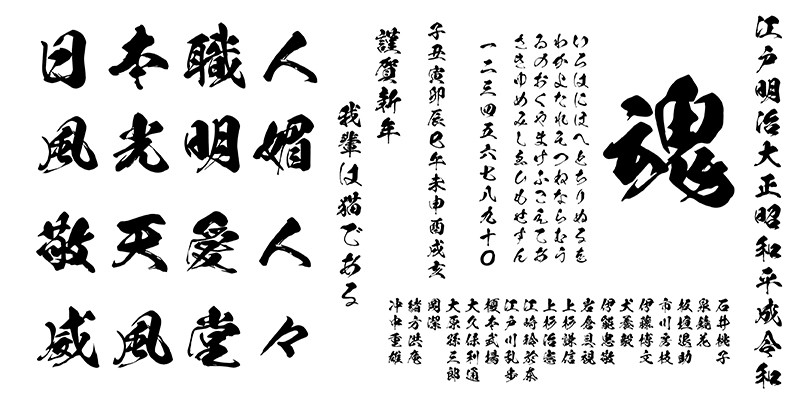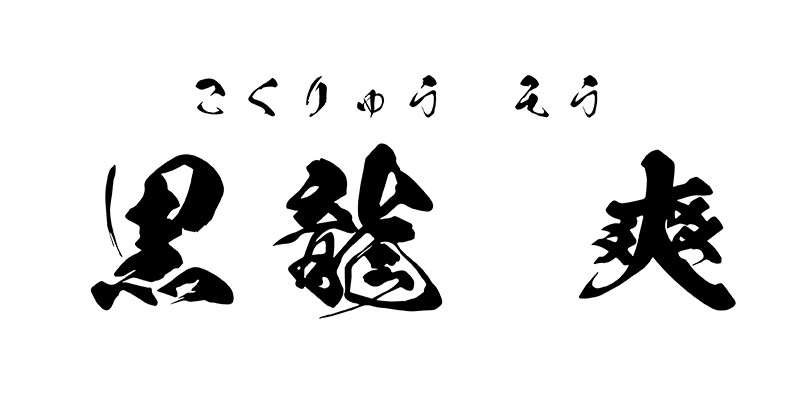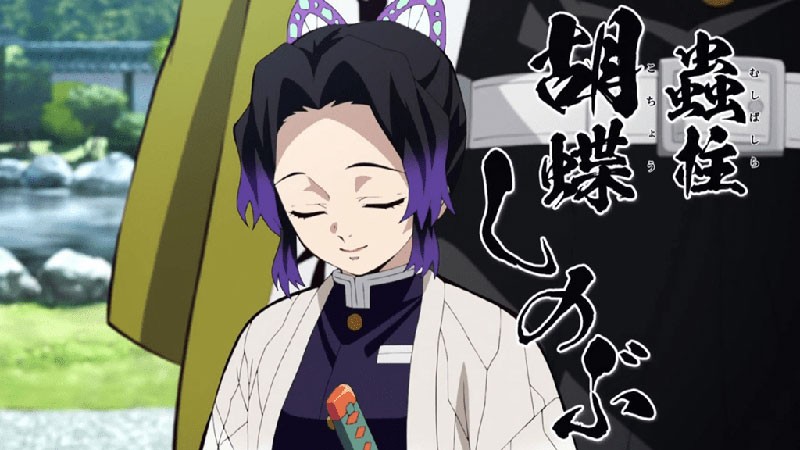
KokuryuSou《鬼灭之刃》动漫字体
Kokuryu-sou(黑龙)是一款高质量书法风格的日文字体,由 Eisen Tsunanori 綱紀栄泉 设计,手写绘制赋予了字体不平衡的特质。然而,当这些字母组合成文字时,却展现出强烈而和谐的视觉效果。ps字体名KSO黒龍N
KokuryuSou《鬼灭之刃》动漫字体
Kokuryu-sou字体还被广泛应用于热门动漫《鬼灭之刃》中,霸道的书法风格为动漫中的文字呈现带来了生动的表现力,增添了独特的视觉风格。
KokuryuSou《鬼灭之刃》动漫字体
这种完全纯手写没有经过电脑标准化的字形很少见,当特定场景的情感文案特别棒。